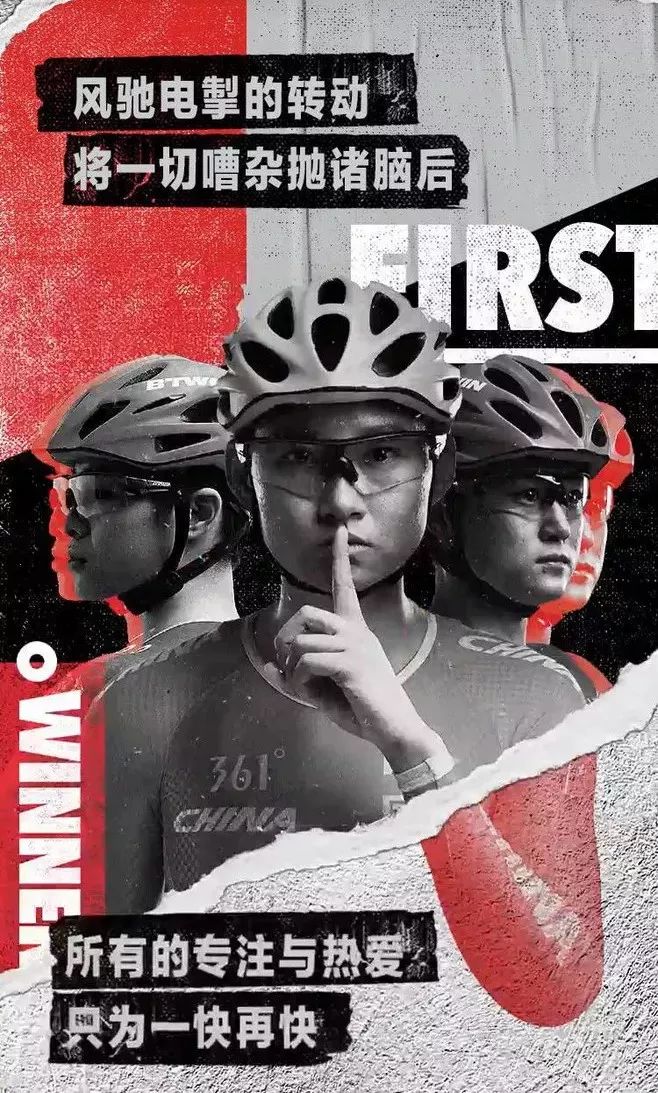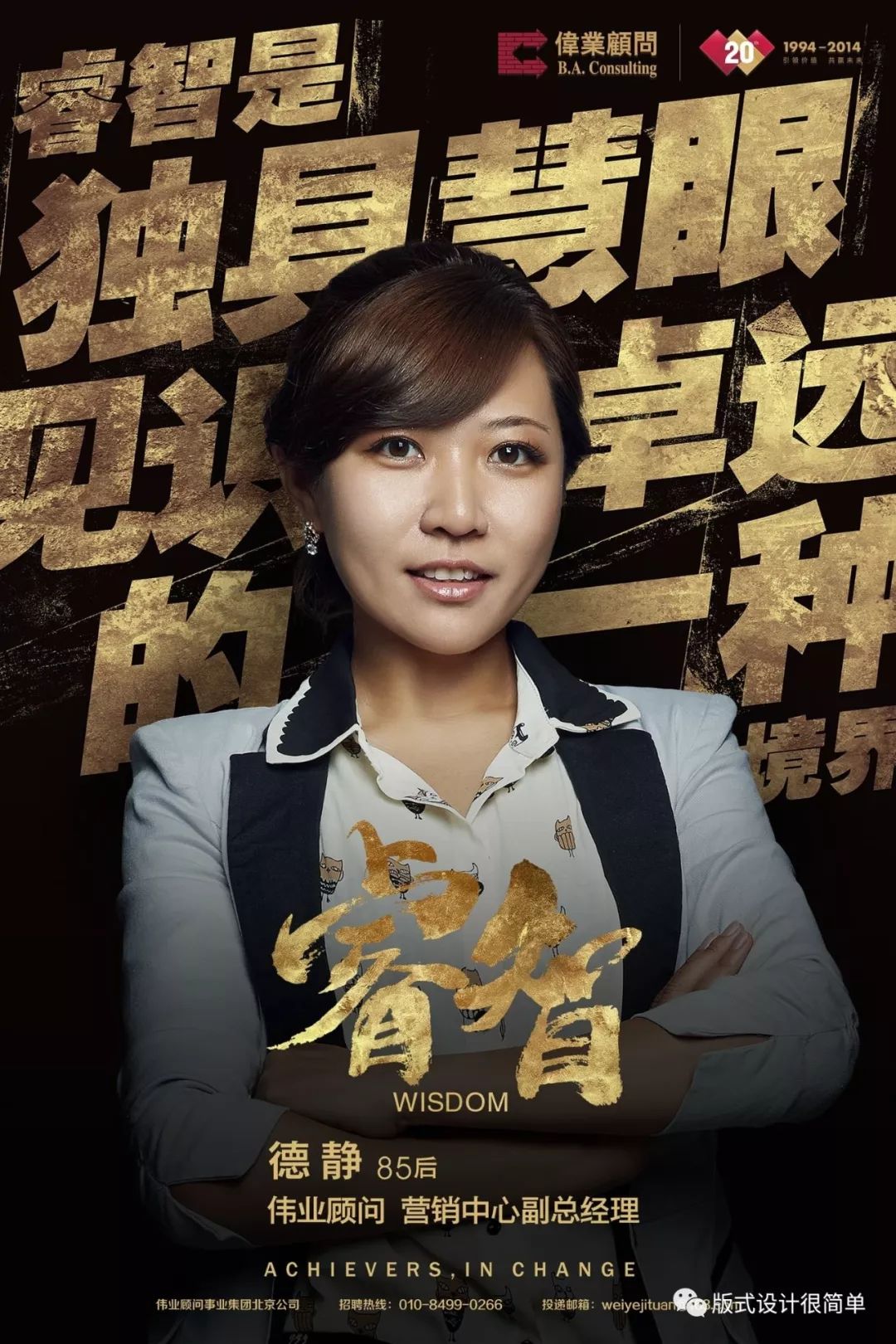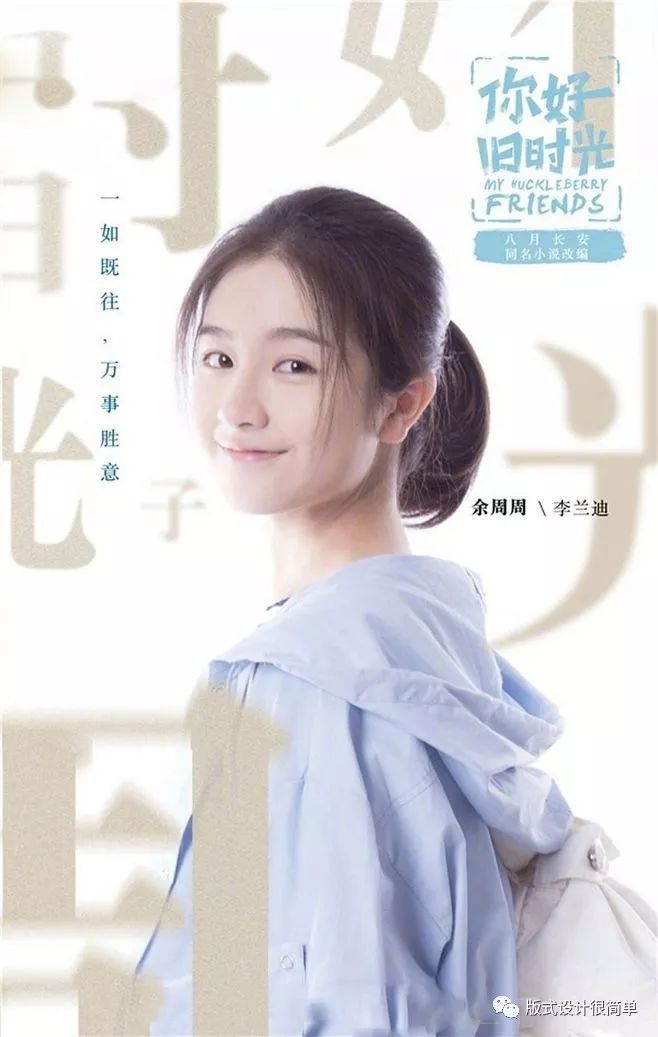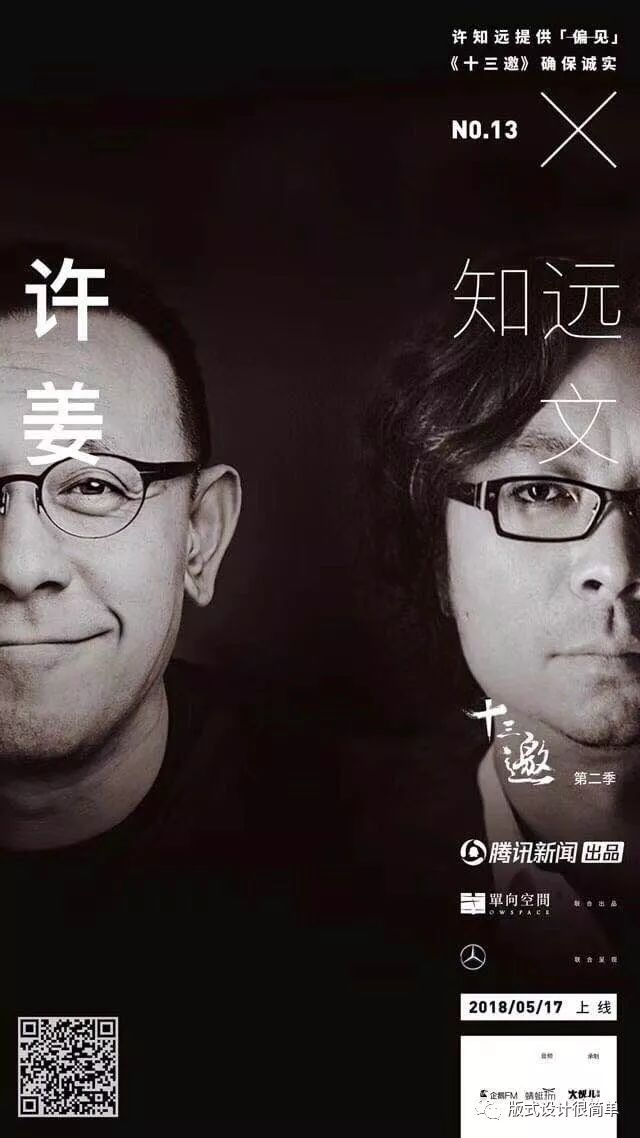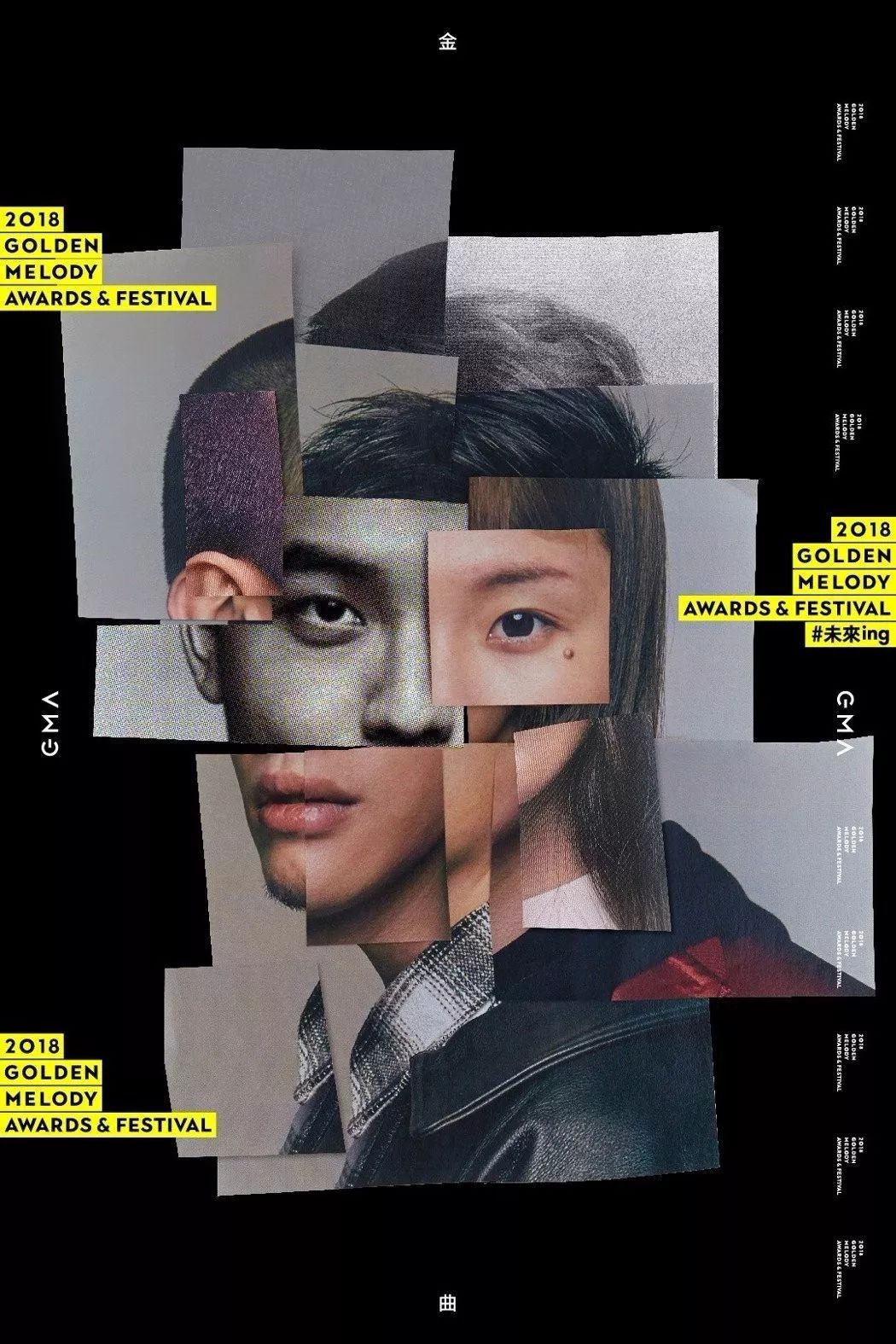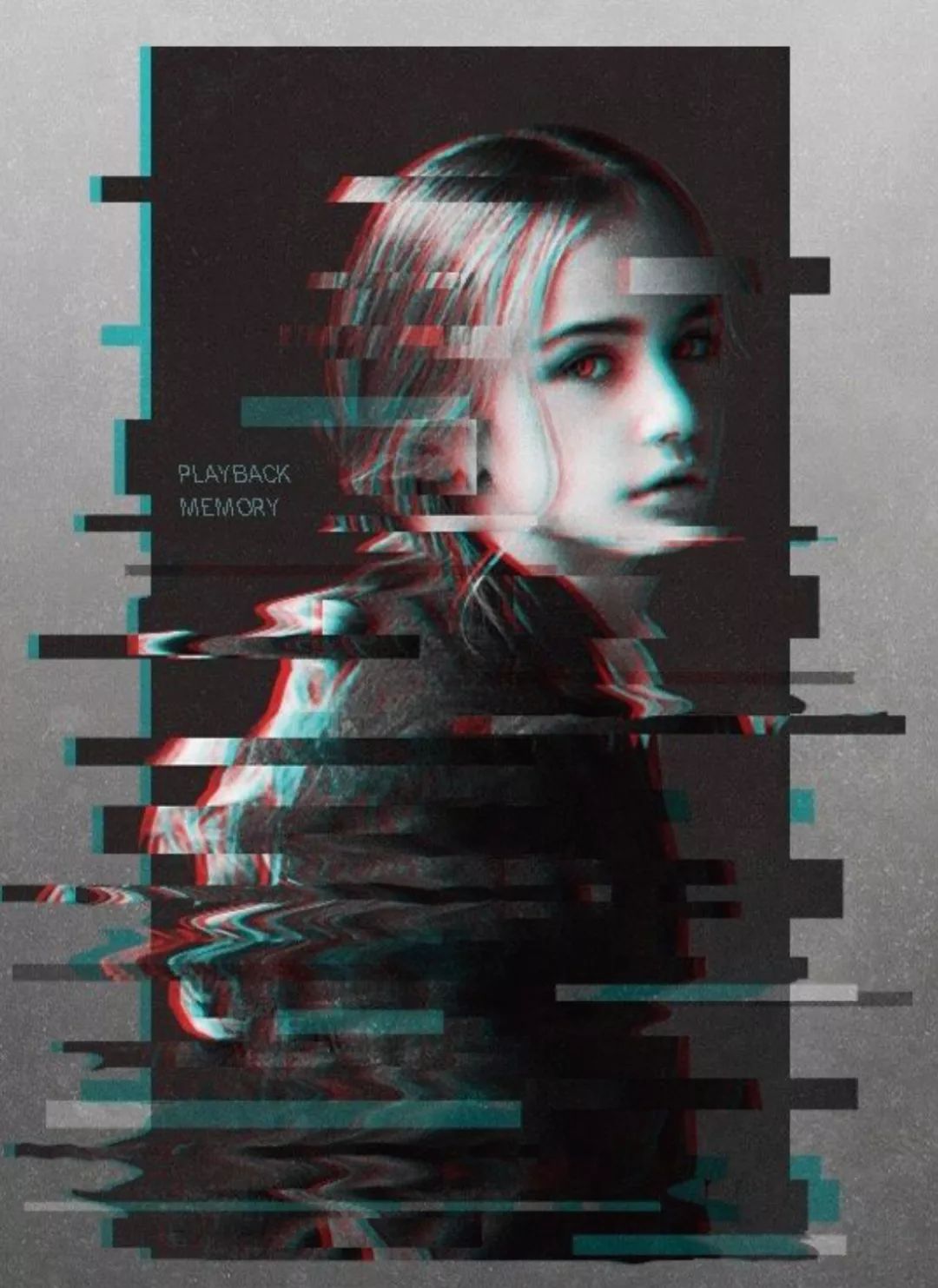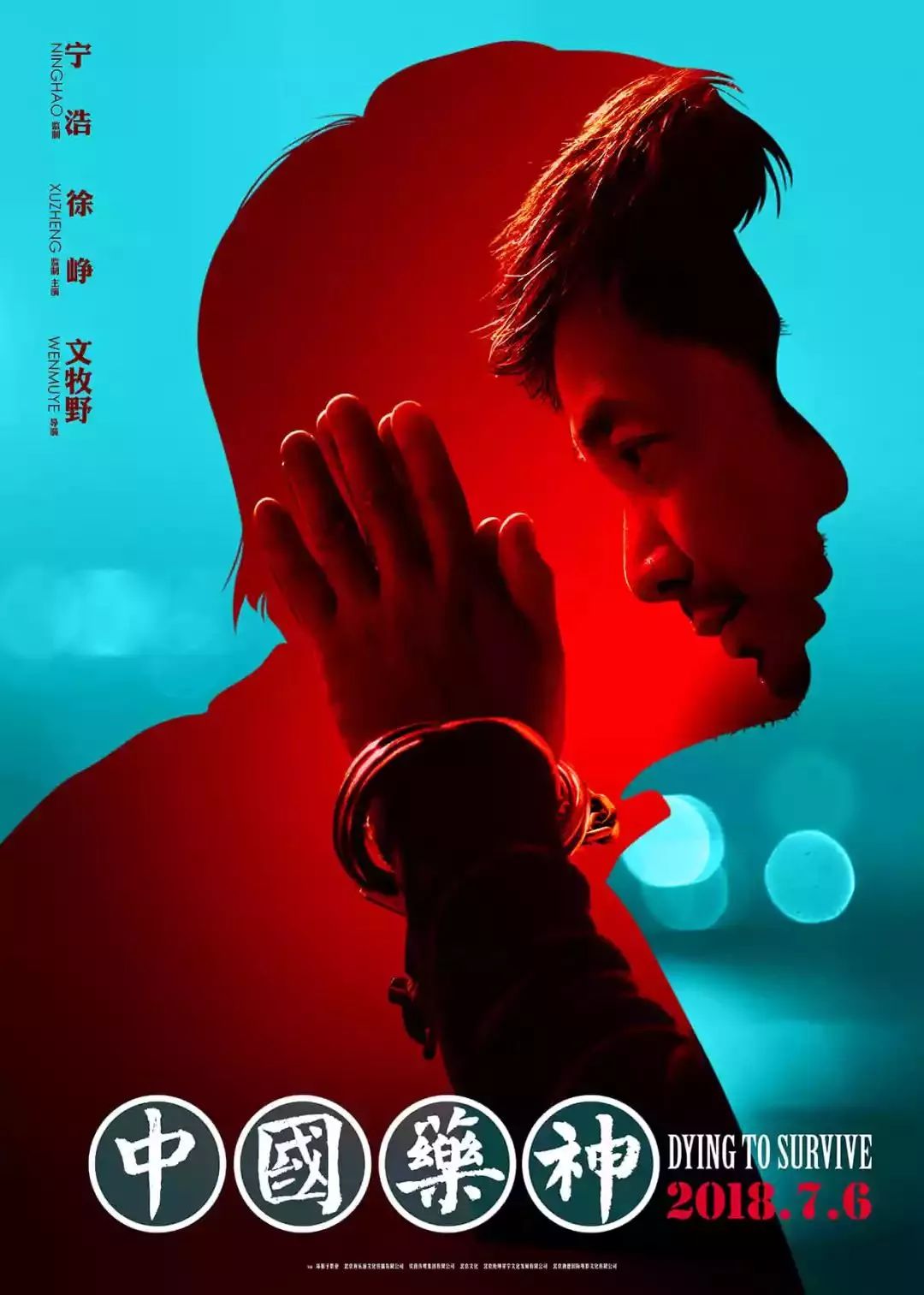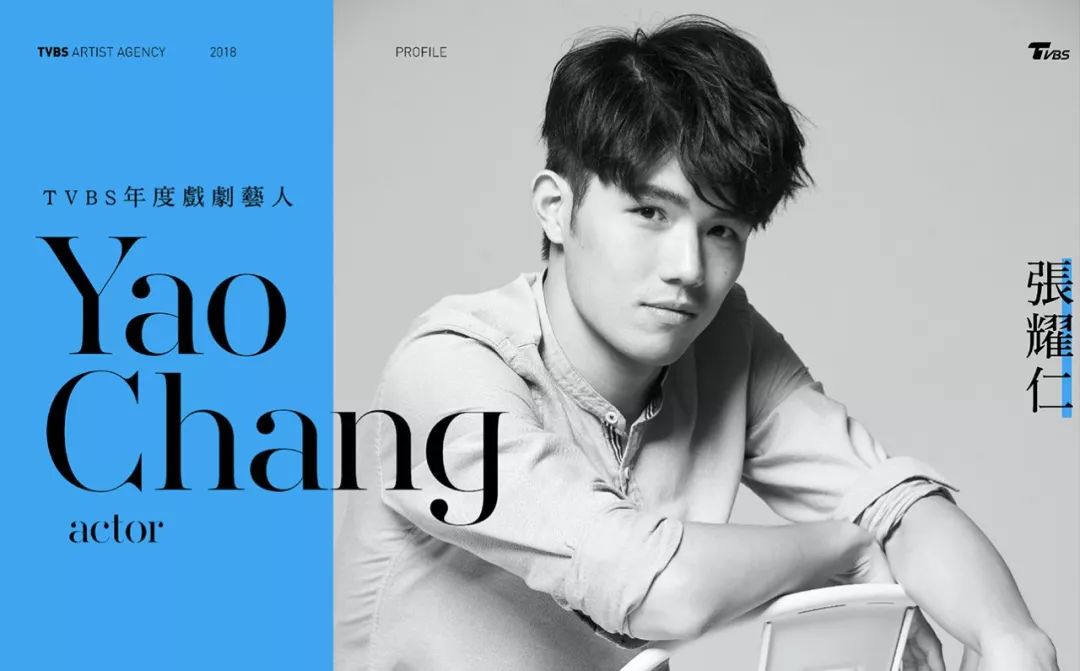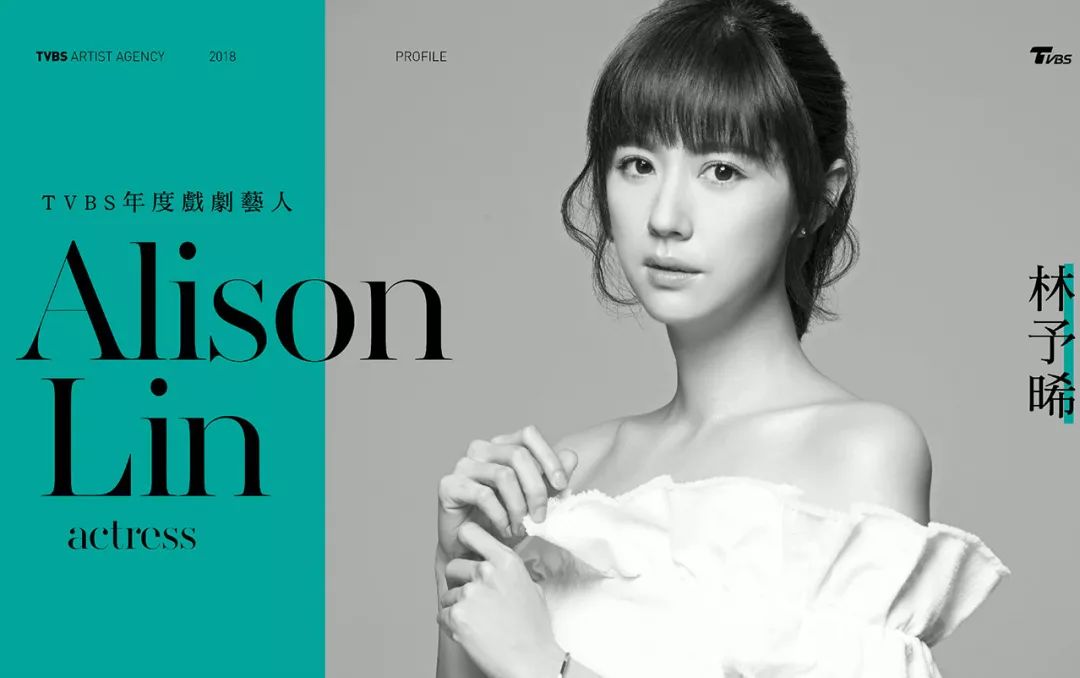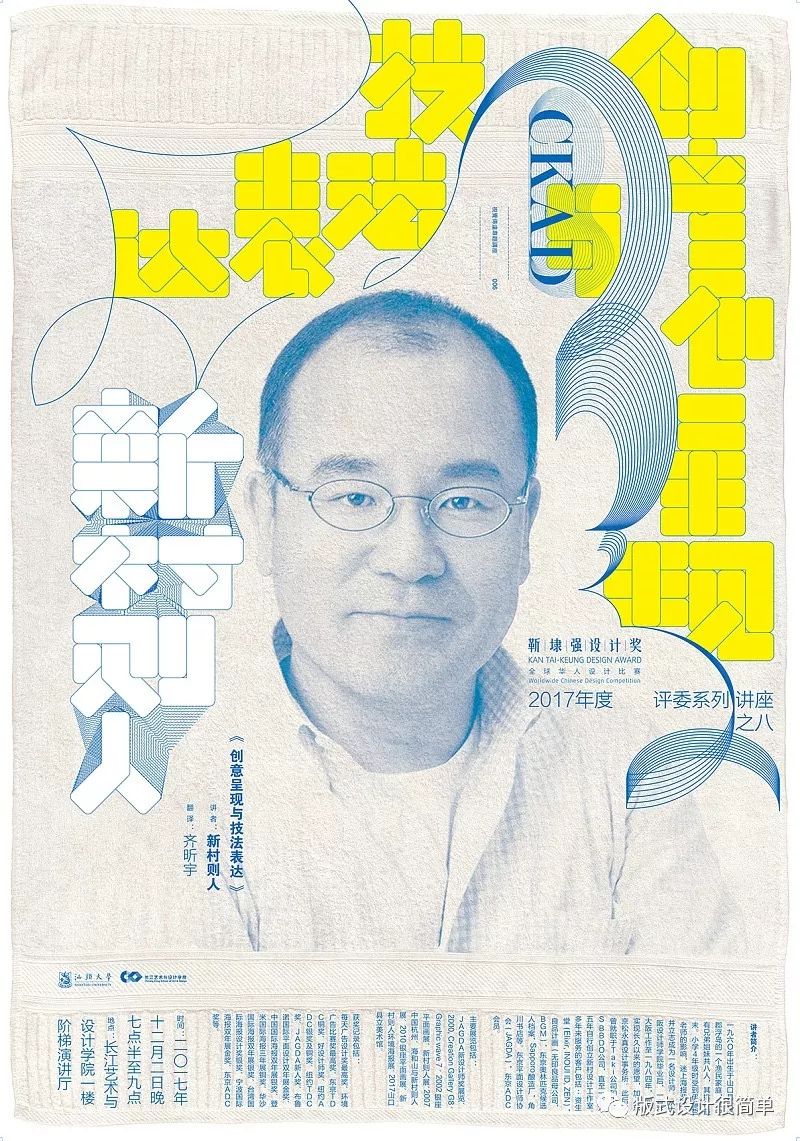
人物海报设计技巧,人物海报怎样做才不显得low?
人物海报一般都是由人物图像和文字设计构成的。这种图文混排的设计有一个共性:第一视线会被人物图像所吸引,然后慢慢转移到文字内容上。一幅好作品给人的印象很大部分取决于人物图像的风格和内容。当然,如果能利用各种元素,也有利于凸显作品主题。今天,我们一起分享设计人物海报的方法。
01 尝试不同的艺术效果
如果尝试不同的艺术效果应用在平面设计上,瞬间给画面带来不一样的艺术效果,更能提高画面丰富性。那么艺术效果指设计者对主题的理解,对创作手法的运用、信息传达的手段、对艺术语言的驾驭等独创性表现。
斑驳做旧艺术效果
撕纸艺术效果
拼贴艺术效果
故障艺术效果
02 借助文字
文字运用在编排中是必不可少的。如果觉得版面太过单调,可以试试图片压字的处理方式,将文字作为背景,主图直接编排在文字上。又或者文字与图形穿插组合,使其成为图形创意的一部分。整体达到图文并茂、别具一格的版面构成形式。提高辨识度与趣味性,同时传达图文两种信息。
03 黑白主题
黑白是永恒的最佳设计拍档。黑白听上去让人觉得僵硬单调,再加上中国的某些传统观念,认为黑白是不吉利的。实际上恰恰相反,它们有一种时尚简约的美,甚至给人高贵优雅的感觉。通常将图片调成黑白状态,利用大面积中性色作为主色。然后再添加某个单色,主角色在这里就起到聚焦突出的作用,能形成强烈对比和统一平衡的效果。
04 双重曝光效果
双重曝光的效果一直深受摄影师的欢迎,也是设计师和艺术家们经常使用的一种相对经典的图片设计制作技巧。而这些双重曝光的海报效果,看起来都创意感十足很有艺术感,其实做起来也没有很困难哦。
05 转换为插画元素
插画形式可以理解为拍摄以外的点线面图形组合,也就是经过手绘处理的图形。插画的好处在于它具有丰富的想象力和自由创造性。
06 大胆的创意与配色
当你选用夸张的创意以及配色时,便会有一种强大的视觉冲击力油然而生。对受众产生着影响,他们会被画面所传递的情绪和能量所吸引。要打造此效果,文字越少能量越大。